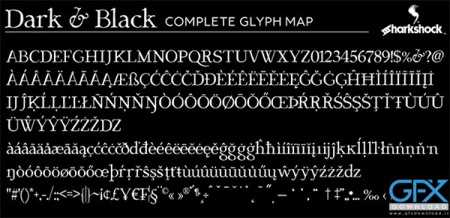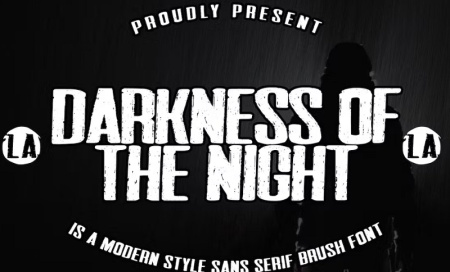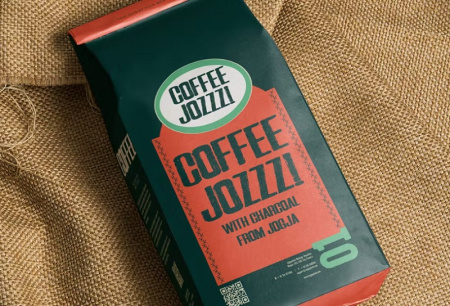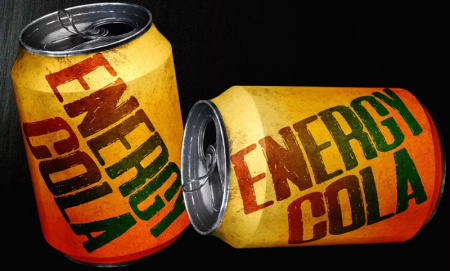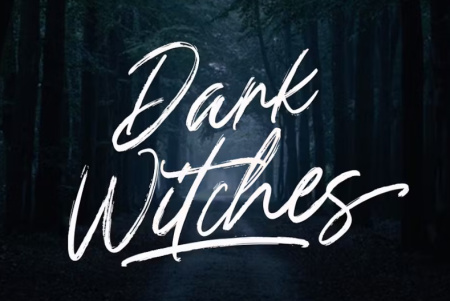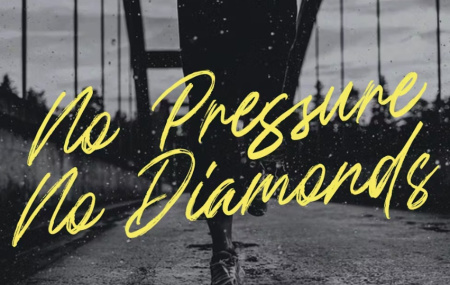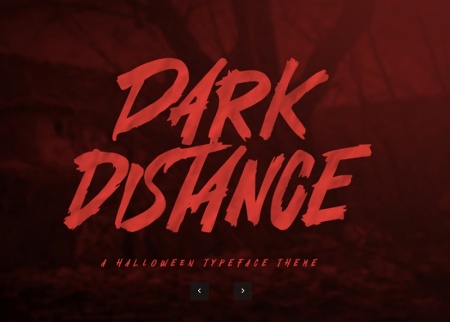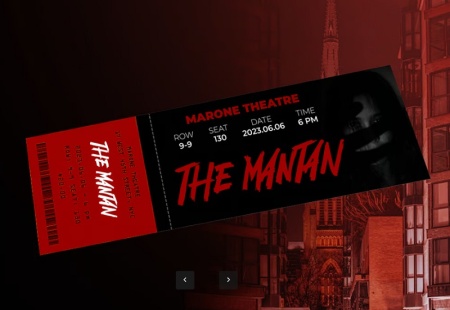
فونت انگلیسی Dark & Black شامل 4 فونت انگلیسی از جی اف ایکس دانلود می باشد. دانلود فونت انگلیسی دارک dark black شامل حروف لاتین پایه، لاتین توسعه یافته، اعداد، علائم نقطه گذاری می باشد. از آن برای جلد کتاب، پوستر فیلم ترسناک یا تزئینات هالووین استفاده کنید. میتوانید این فونت انگلیسی را با تهیه اشتراک ویژه از جی اف ایکس دانلود تهیه نمایید.
2- فونت انگلیسی دارک
این فونت انگلیسی با تم تاریک و شب با نام Darkness Of The Night می باشد. این فونت انگلیسی دارک مناسب برای لوگوها، نقل قول ها، پوسترها، تبلیغات و هر طرح دیگری که نیاز به تم دارک دارد، عالی است. این فونت با فرمت های TTF - OTF و WOFF ارائه شده است.
3- فونت دارک انگلیسی Dark Distance
Dark Distance یک فونت با تم دارک و ترسناک برای طراحی های هالووین، لوگو، برند تجاری، کارت تبریک، پوستر و ... می باشد. این فونت انگلیسی دارک با فرمت otf و ttf ارائه شده است.